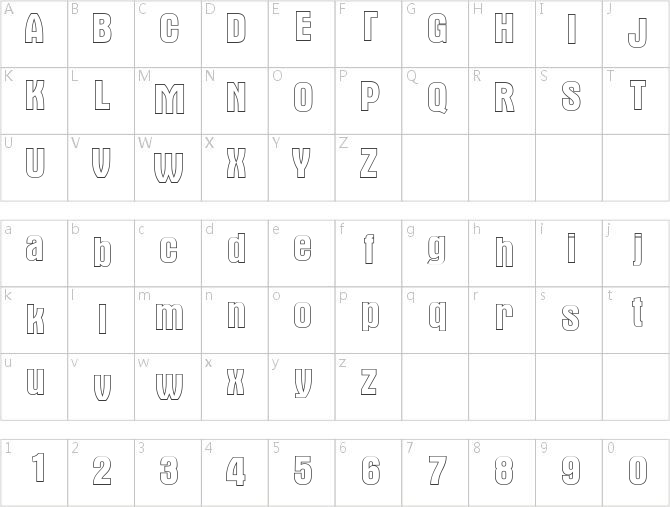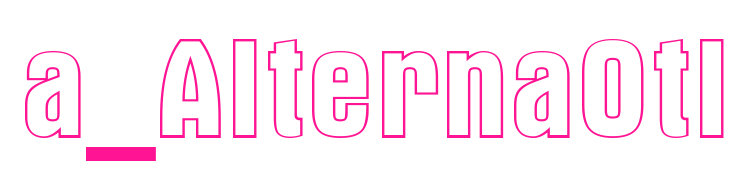
a_AlternaOtl 詳情頁(yè)
a_AlternaOtl字體字庫(kù)是一款讓人賞心悅目、百看不厭的英文字體,適合各類廣告和產(chǎn)品包裝設(shè)計(jì)應(yīng)用,字體大小0.06MB,格式為ttf字體,上傳用戶是13226568769,作者/版權(quán)方為未知